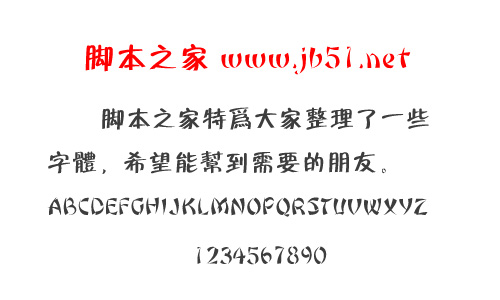
方正氈筆黑繁體字體是方正字體庫中的一種字體,方正氈筆黑是一款具有POP風(fēng)格的創(chuàng)意手寫字體。這款字體的筆畫形態(tài)是對氈頭筆書寫特點的幾何概括,起筆處呈圓形,橫筆畫左粗右細(xì),字形結(jié)構(gòu)整體右上傾斜,富有動感。方正氈筆黑的風(fēng)格干凈利落,易讀性強,尤其適用于時效性的廣告設(shè)計,以及兒童類品牌的產(chǎn)品包裝設(shè)計。喜歡的朋友們可以前來下載使用。